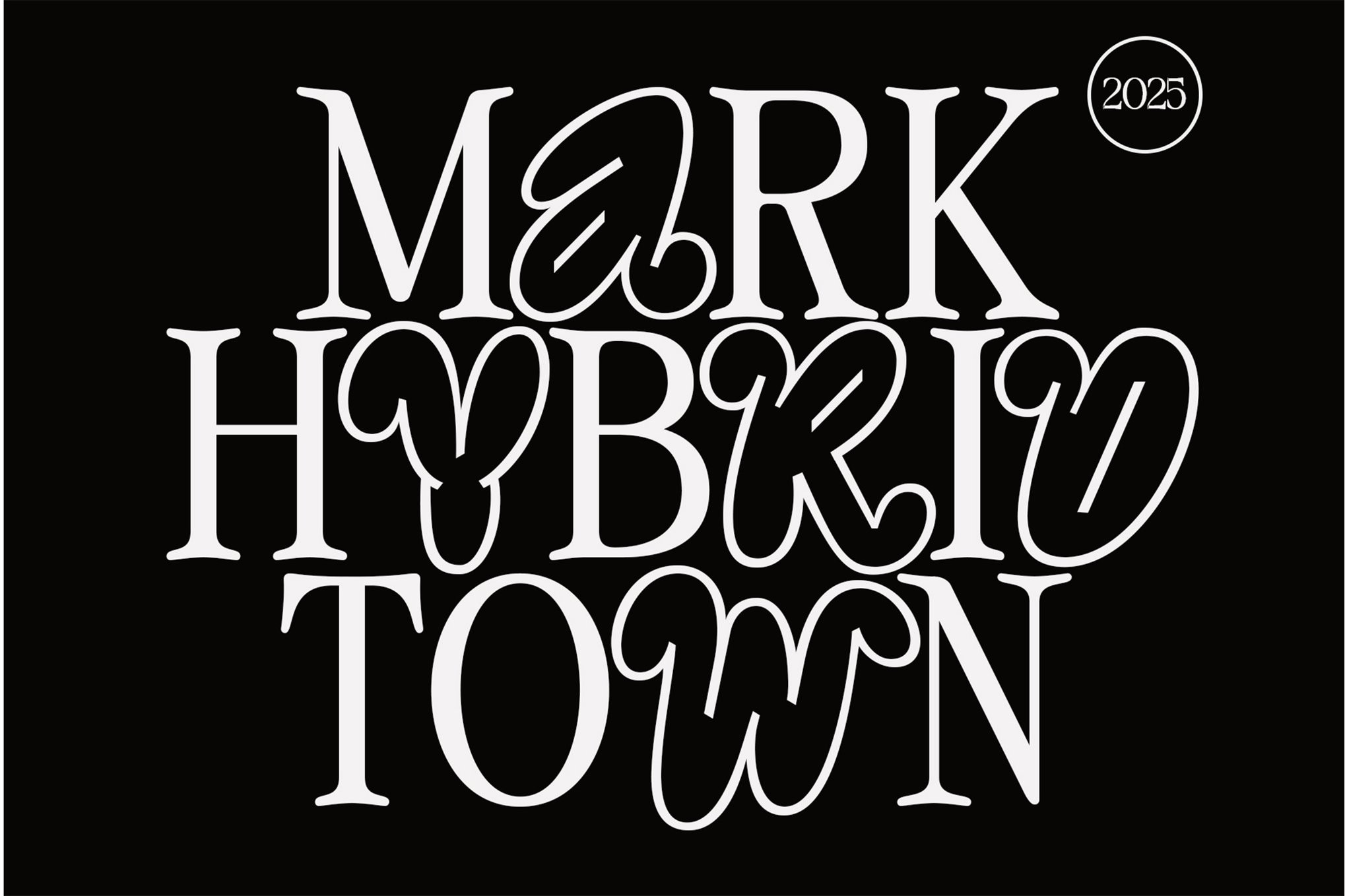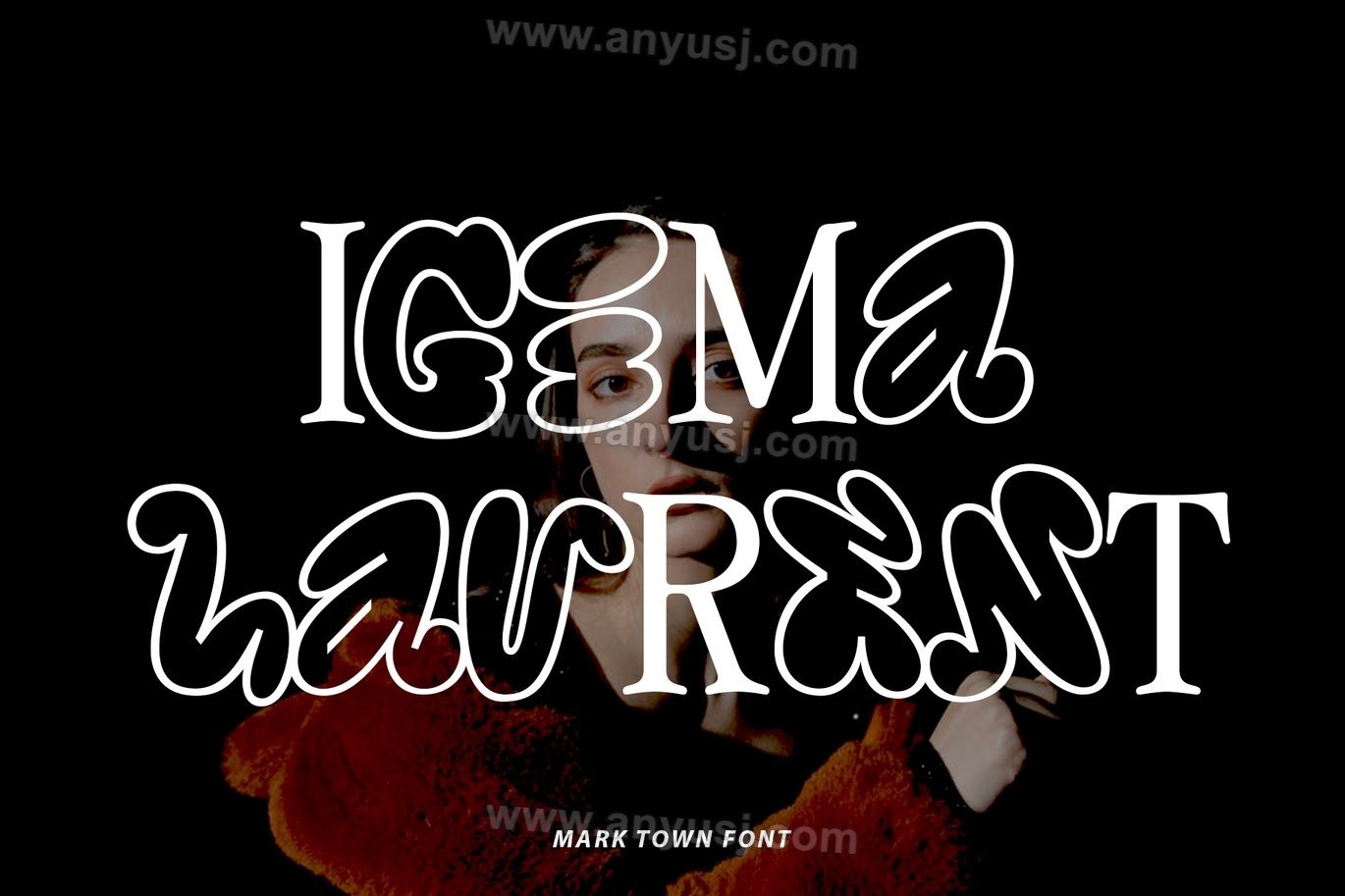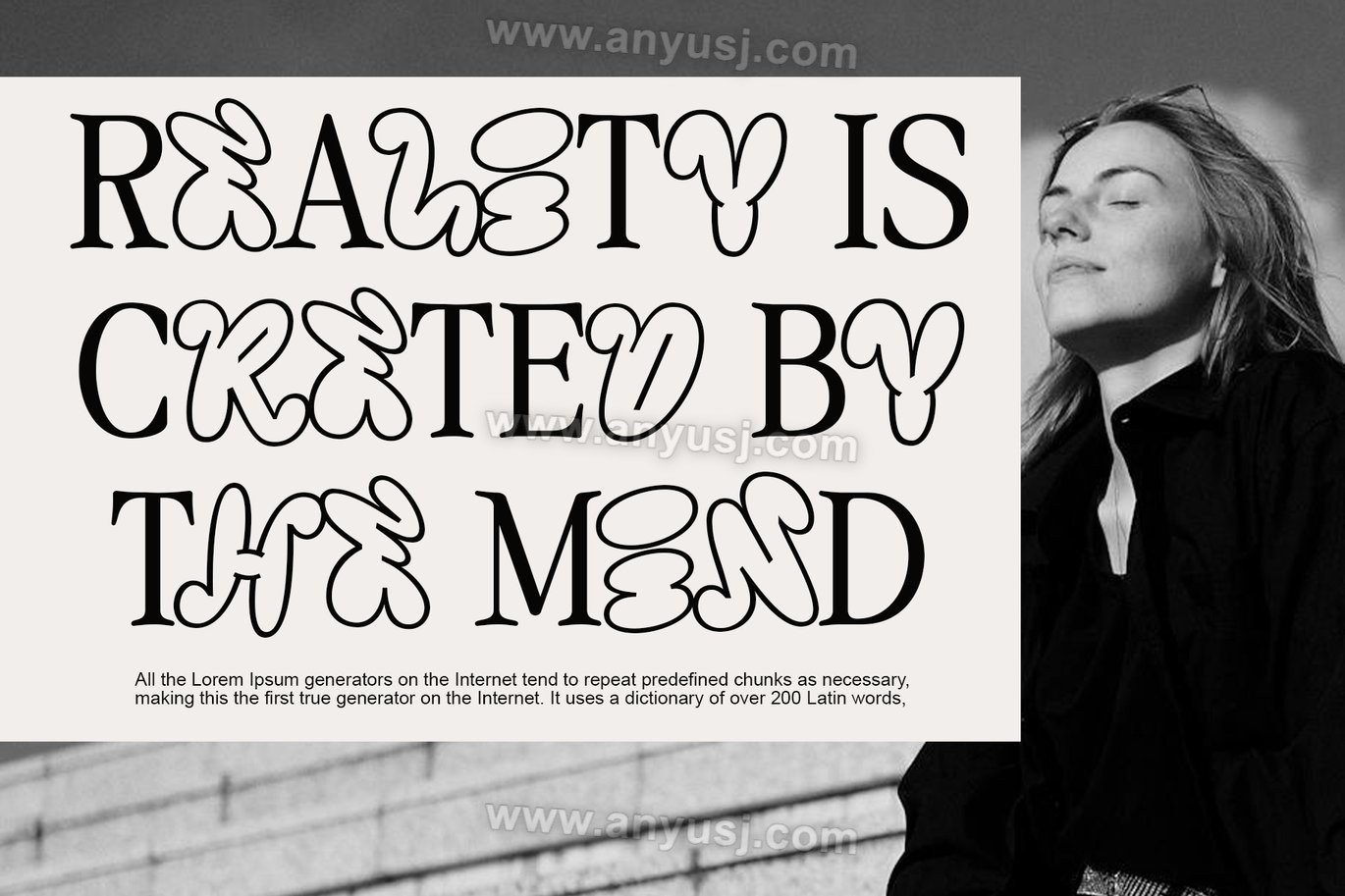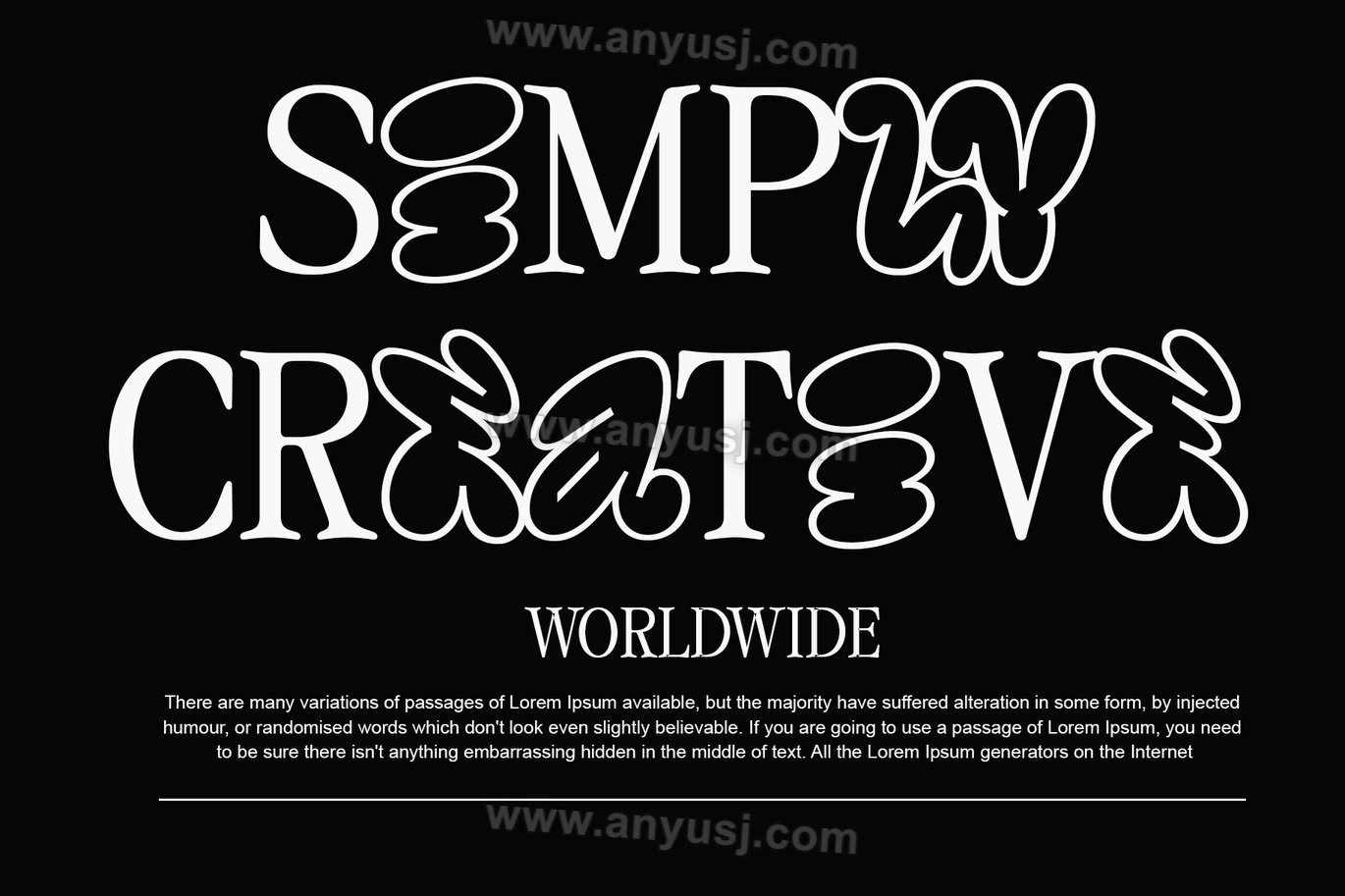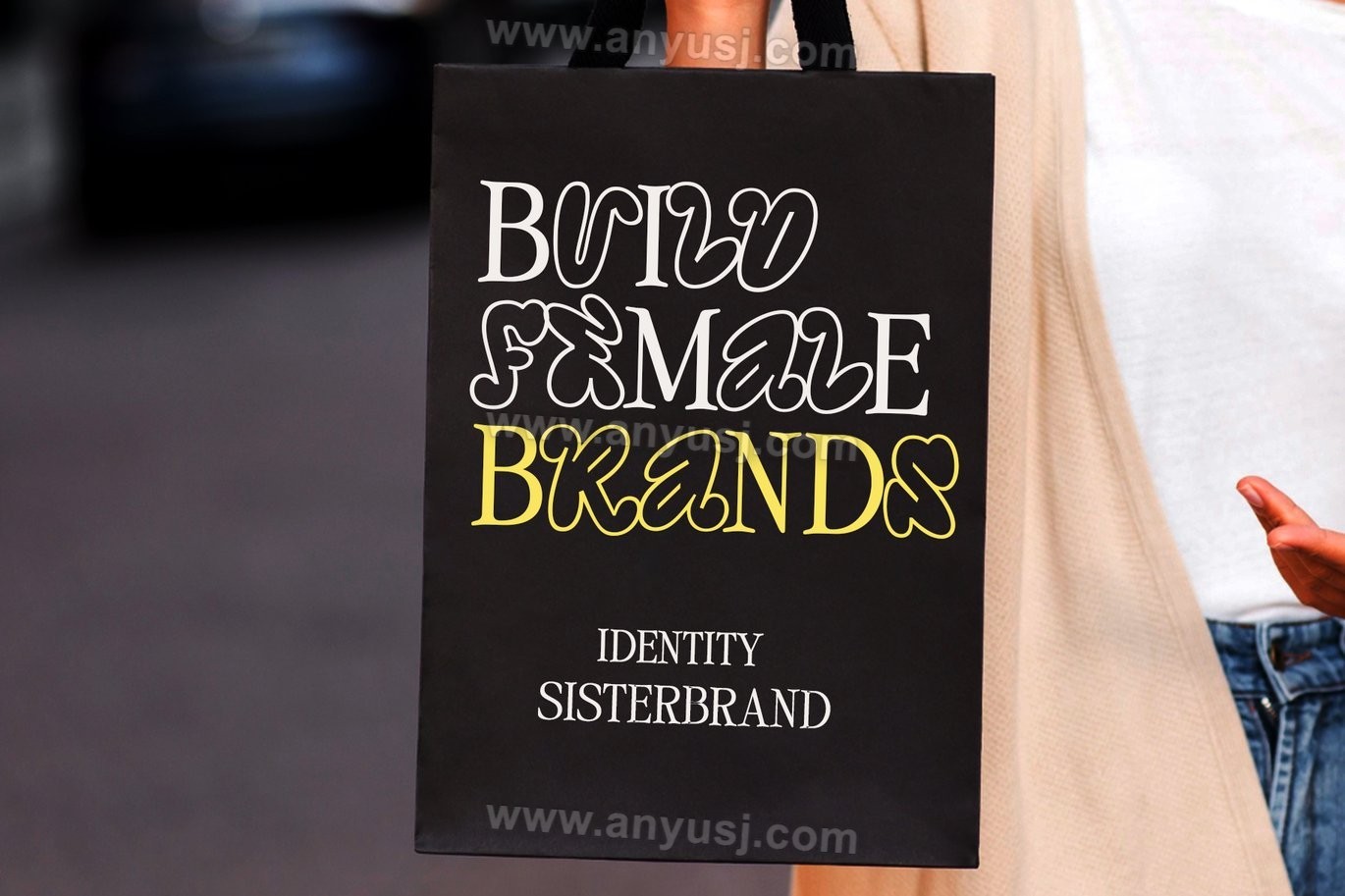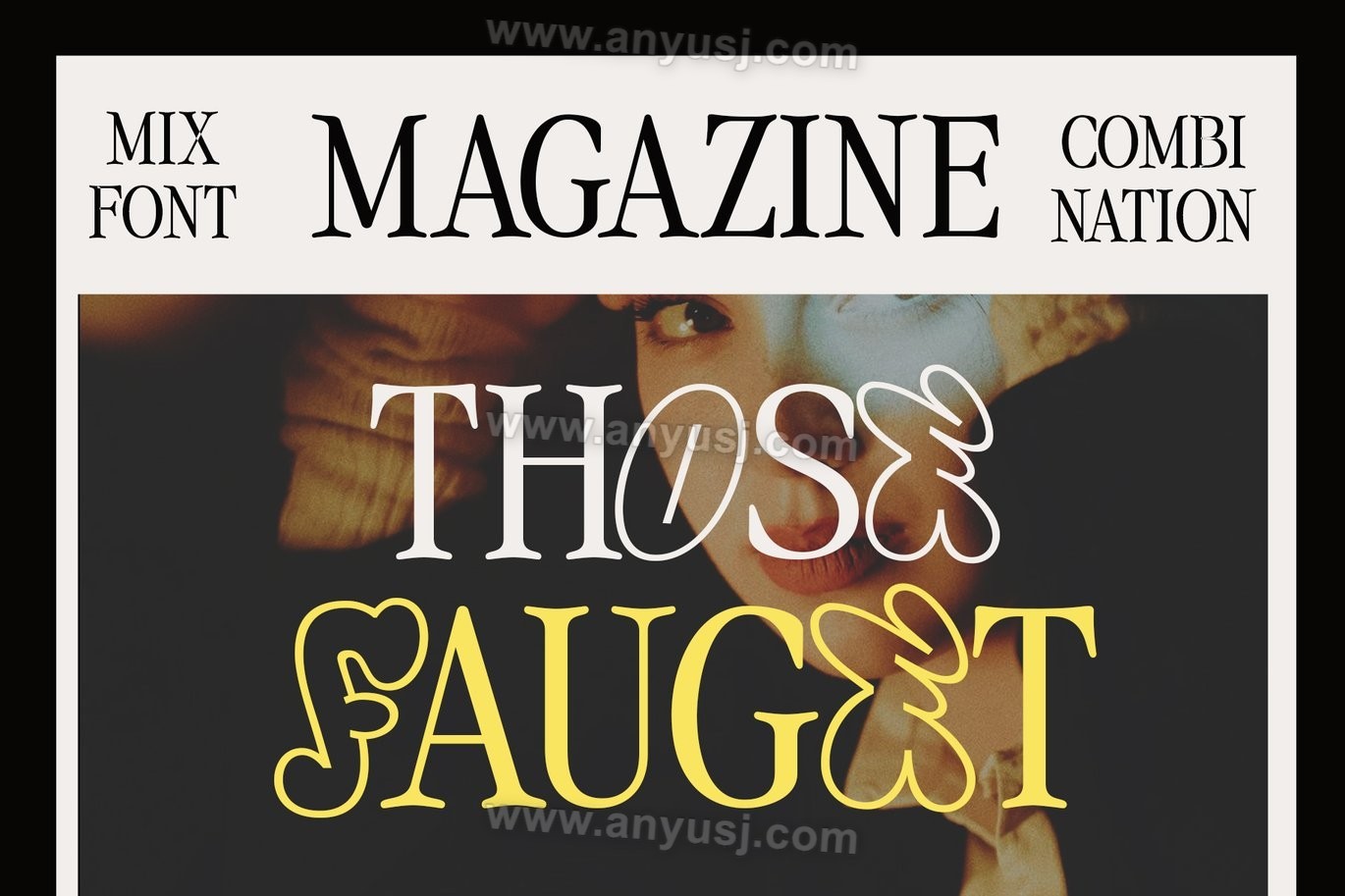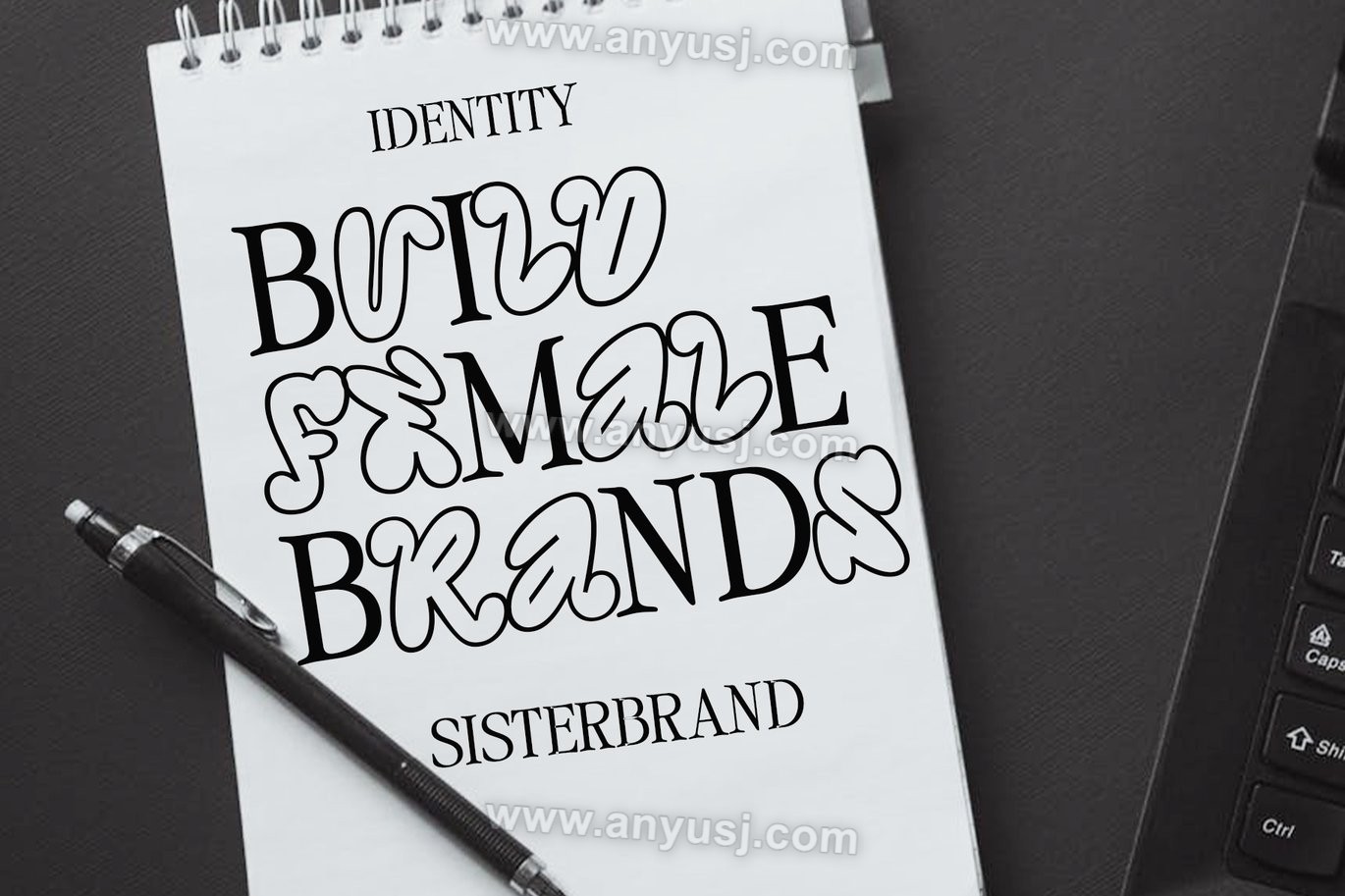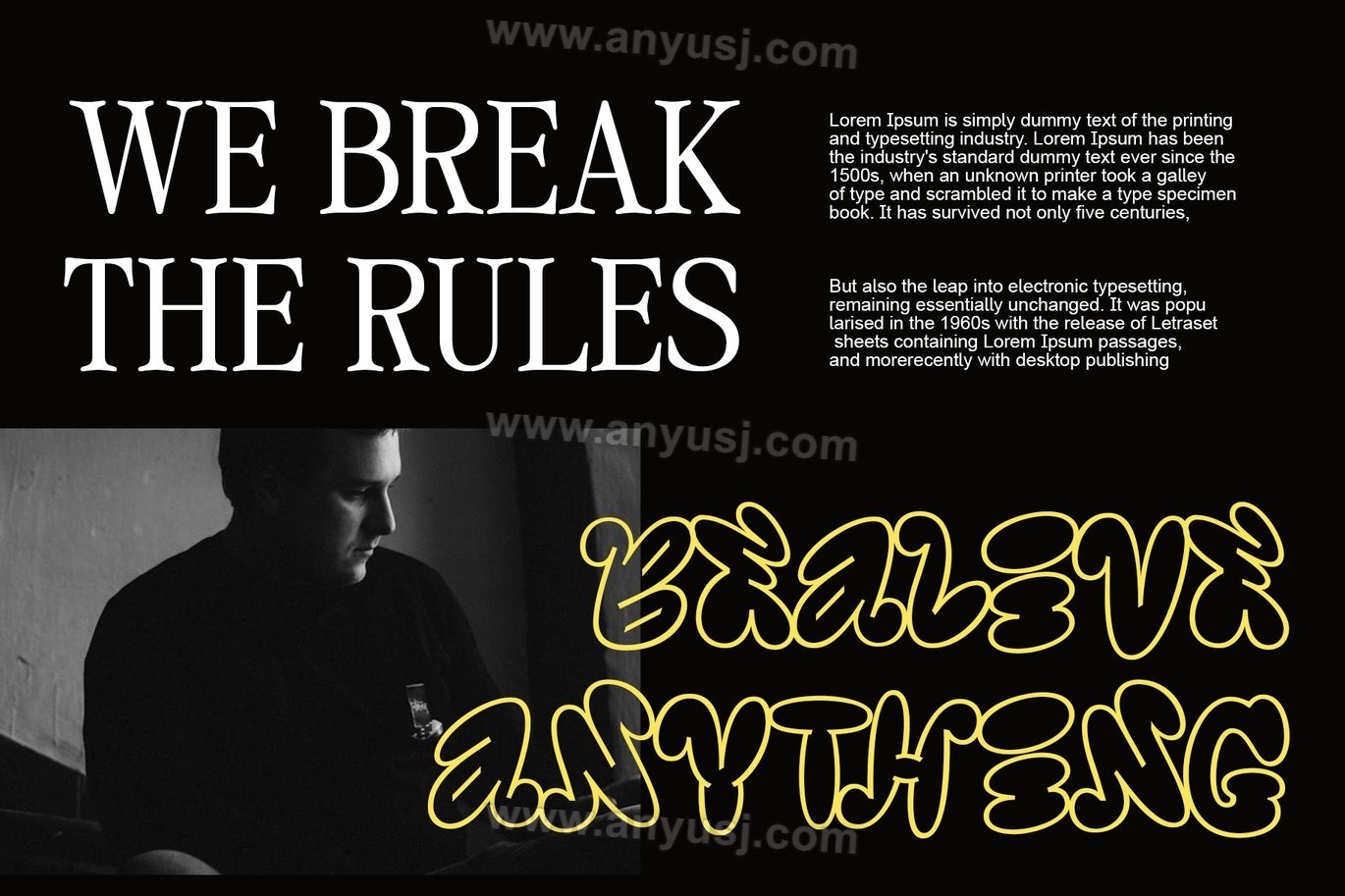
复古Y2K气泡衬线logo标题排版西文英文字体组合Mark Town
Mark Town采用混合排版风格,将两种截然不同的字体风格结合在一起。所展示的印刷品优雅、坚固、正式。给人一种俏皮、现代和实验的感觉。Mark Town非常适合现代设计项目、实验品牌、音乐海报或艺术节,这些项目或艺术节想要传达关于多样性、过渡或两个世界融合的信息
大写和小写
标点、数字和符号
多语言支持
OpenType的特点